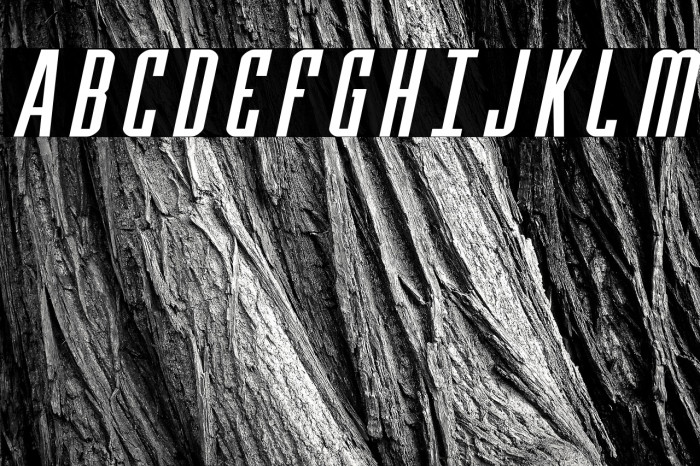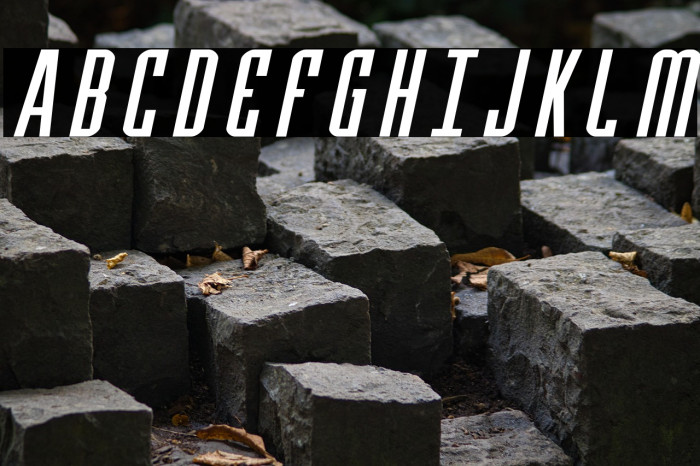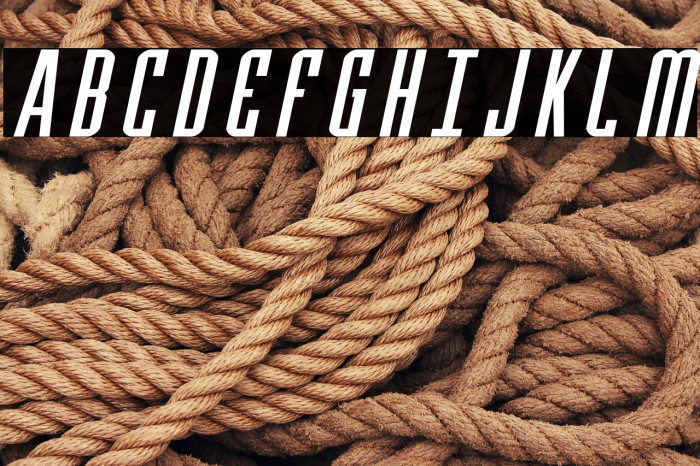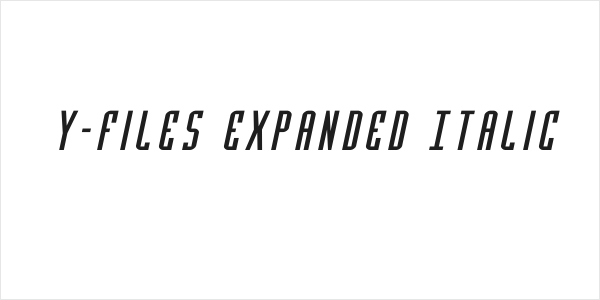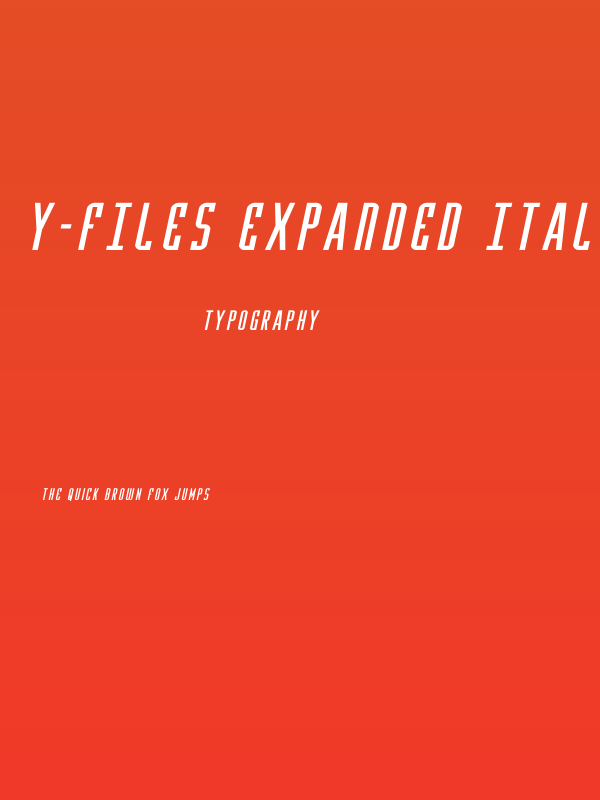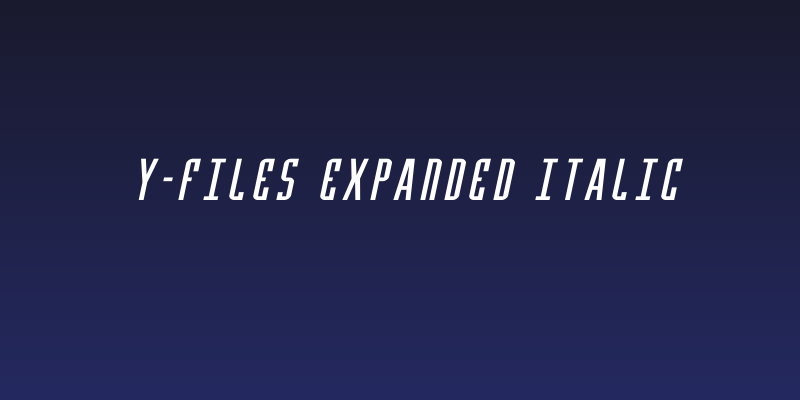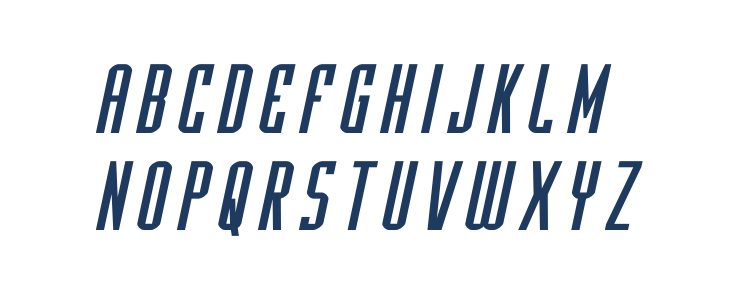
Y-Files Expanded Italic Font
| Larghezza | Expanded |
| Progetti proposti | Ideal for sports branding, dynamic posters, modern advertisements, and futuristic designs. |